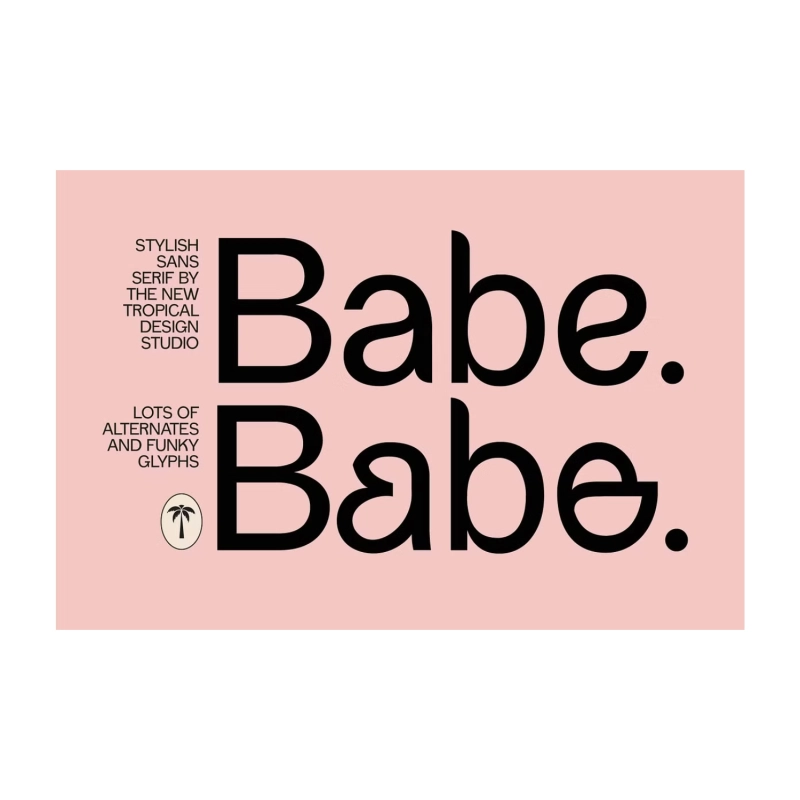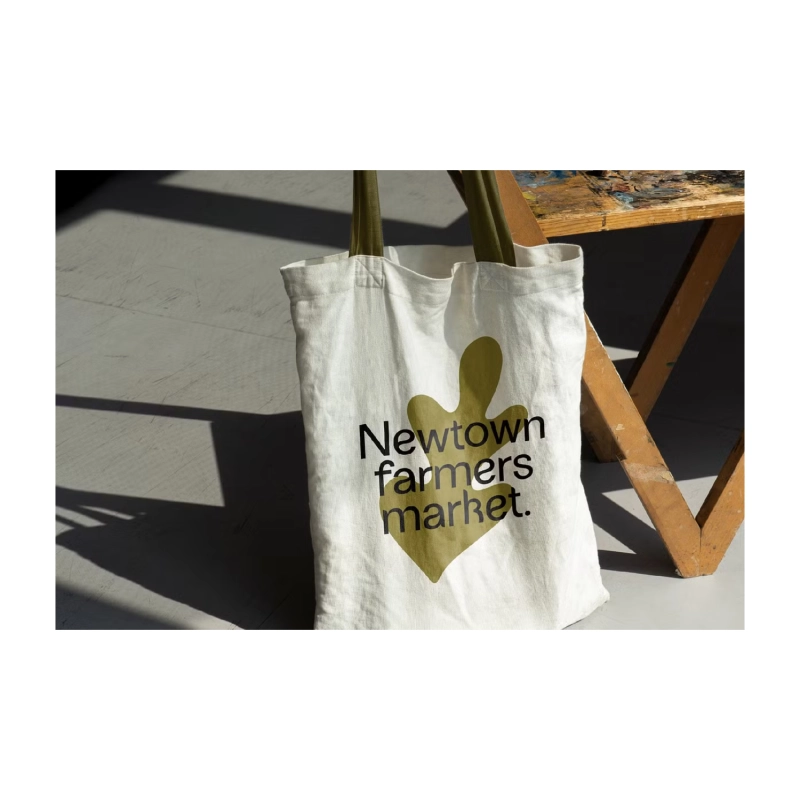
فاتنة - خط بلا شريف
إنها لطيفة ، إنها جريئة ، لديها منحنيات في جميع الأماكن الصحيحة. إنه بيب سانس. إنها نظيفة ومقروءة وحديثة مثل سان الكلاسيكية ولكن هذه الحروف الرسومية لها أسلوب! المنحنيات الرائعة والبدائل غير التقليدية تجعل الخط فريدا لا ينسى.
• الأحرف الكبيرة ، البدائل ، الأرقام ، علامات الترقيم
• دعم متعدد اللغات (بما في ذلك البولندية)